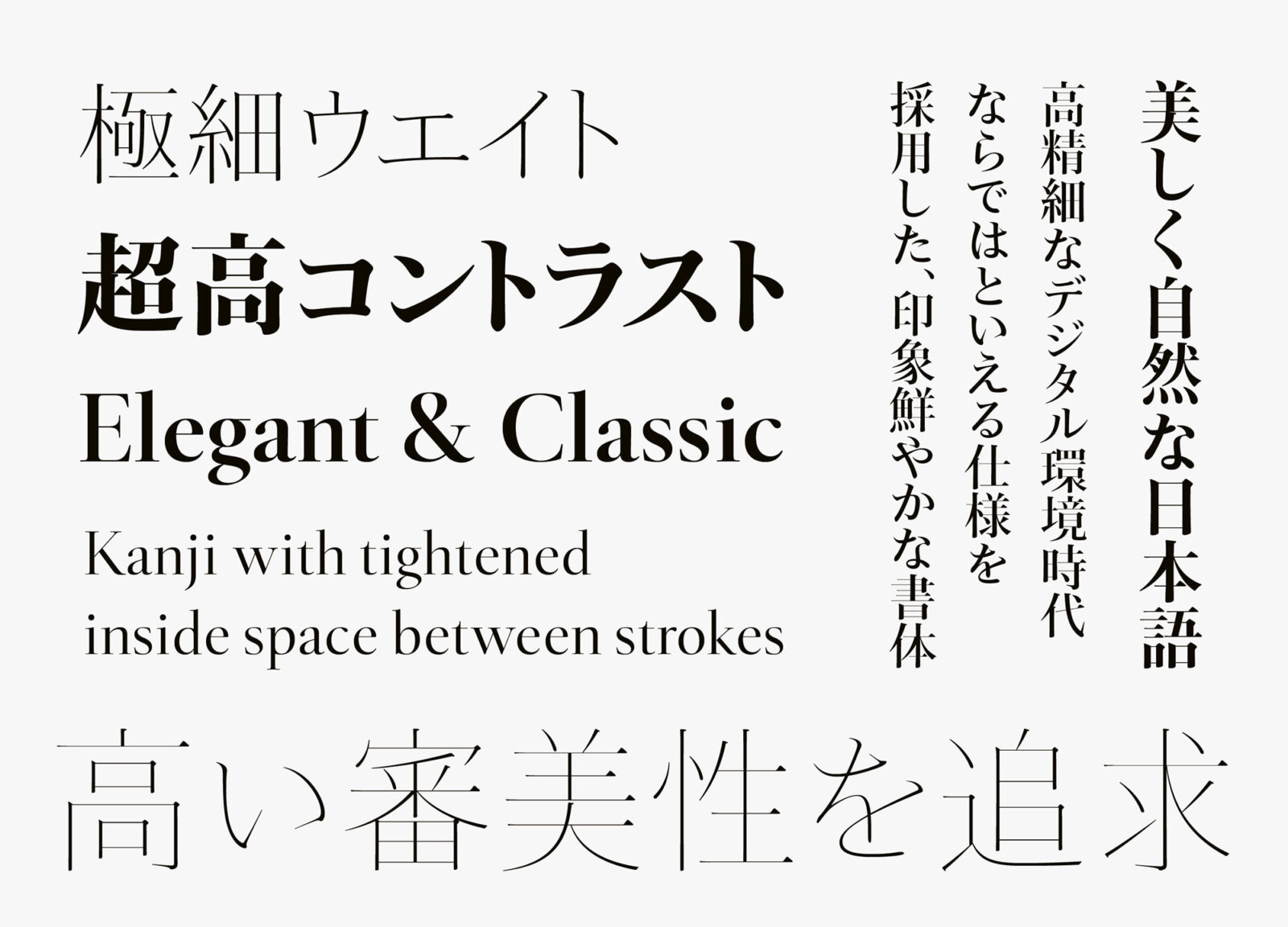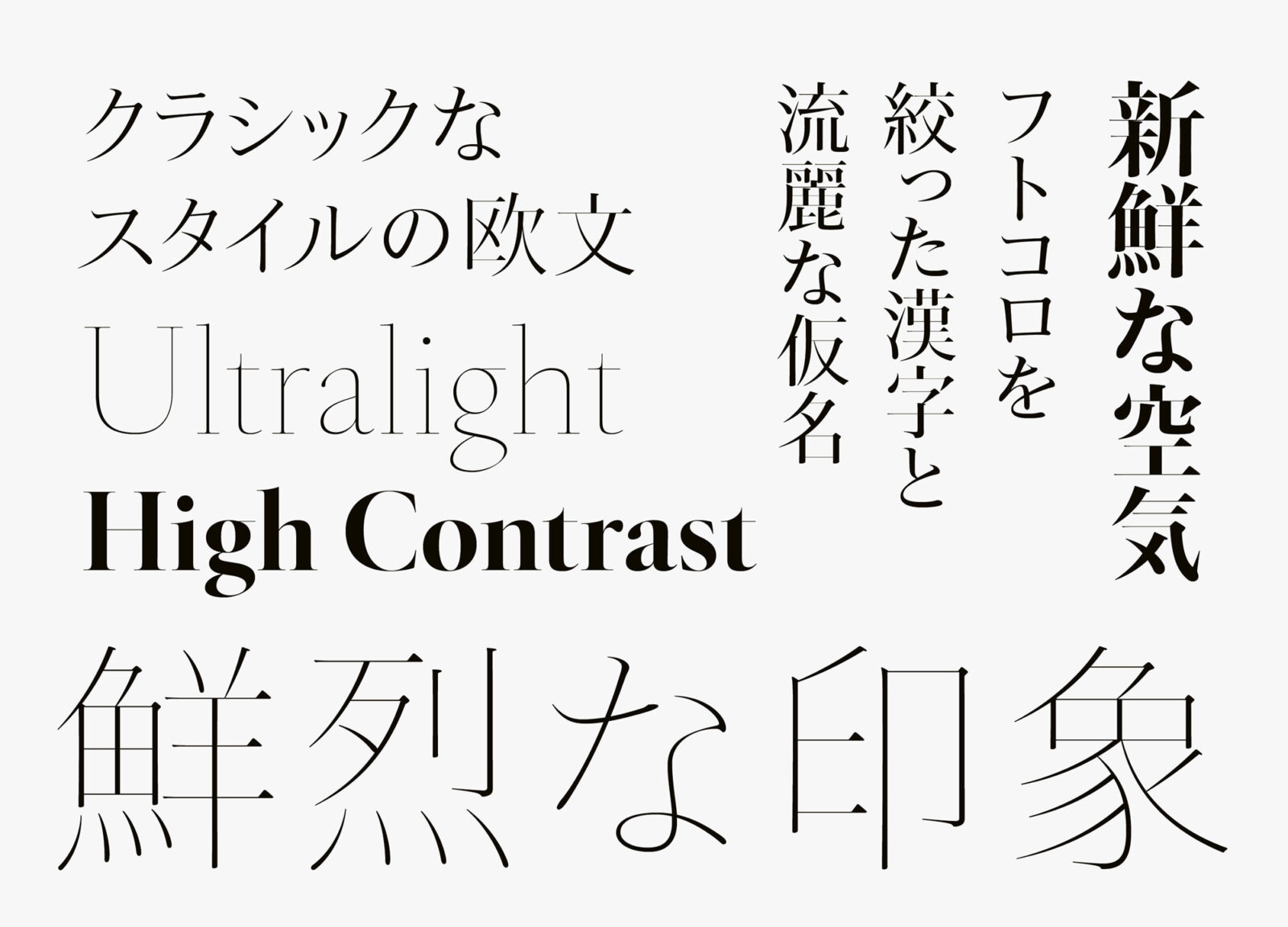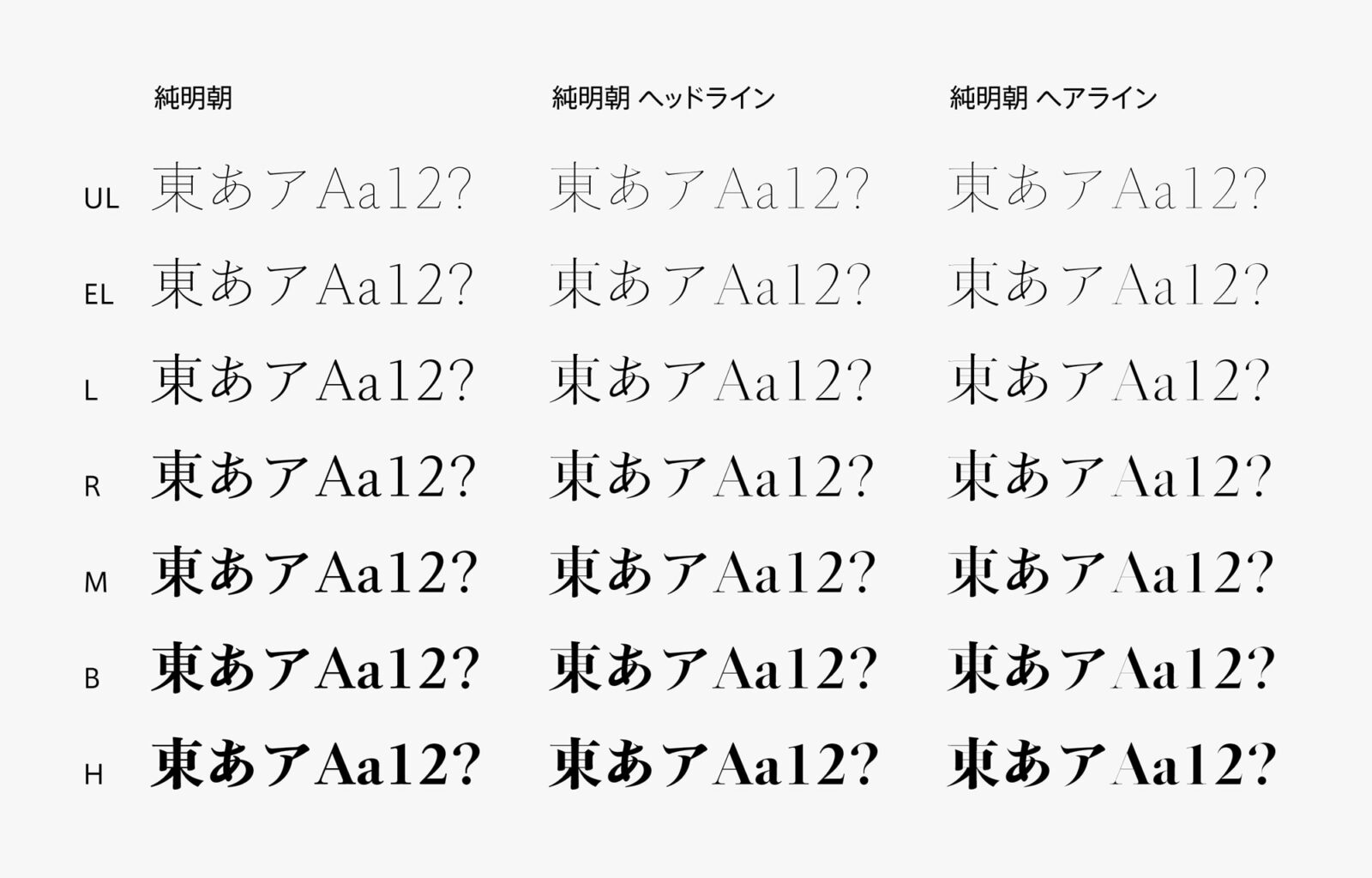
タイププロジェクト、コントラストを極限まで高めた 「純明朝 ヘッドライン」 と「純明朝 ヘアライン」の提供を開始
高精細なデジタル環境時代ならではといえる仕様の印象鮮やかな書体
タイププロジェクト株式会社(東京都練馬区 代表取締役社長 鈴木 功)は、デジタル環境に適した純明朝のシリーズとしてより高い審美性を追求した「純明朝 ヘッドライン」 と「純明朝 ヘアライン」を発表しました。本日よりタイププロジェクトのサブスクリプションサービス「TPコネクト」にて提供を開始いたします。
純明朝 ヘッドラインと純明朝 ヘアラインは、「横組みの日本語をもっと読みやすく、もっと美しく」をテーマにした純明朝シリーズのなかで、より高い審美性を追求するために開発した書体です。オーソドックスで汎用性の高い純明朝に対し、ヘッドラインとヘアラインは、ハライやテンの先端部を細くして縦画と横画のコントラスト比を高め、明朝体ならではの美しさを際立たせています。
純明朝 ヘッドラインと純明朝 ヘアラインは、読みやすくて美しいという純明朝のコンセプトをベースに、見出し用途として思い切った設計をおこないました。フトコロを絞った漢字と長めに残した平仮名の筆脈との相性が良いのはもちろんのこと、クラシックなスタイルの欧文が、優美な和文との調和を見せています。純明朝 ヘッドラインとヘアラインは、高精細なデジタル環境時代ならではといえる仕様を採用した、印象鮮やかな書体です。
タイププロジェクトの代表取締役 鈴木 功は、「純明朝 ヘッドラインとヘアラインは、極細の横画とストローク先端部に明確にその特徴を示しました。汎用性が高く、実用的な役割を果たす純明朝が中核に存在するため、ヘッドラインとヘアラインは、審美性の高さを求める方向にデザインを振り切ることができました。とくに細いウエイトは、タイププロジェクトが得意にしてきた『極細ウエイト、超高コントラスト』のひとつの到達点と言えると思います」と述べています。
純明朝 ヘッドラインとヘッドラインは、UL(ウルトラライト)、EL(エクストラライト)、L(ライト)、R(レギュラー)、M(ミディアム)、B(ボールド)、H(ヘヴィ)の7ウエイトで構成しています。通常の明朝体にはない細さのULとELは、キャッチフレーズやヘッドラインで使用した場合に、強いインパクトを与えます。また、極限まで高いコントラストをもつBとHは、これまでの見出し明朝がもの足りなく感じるほど、鮮やかな印象をもたらすフォントです